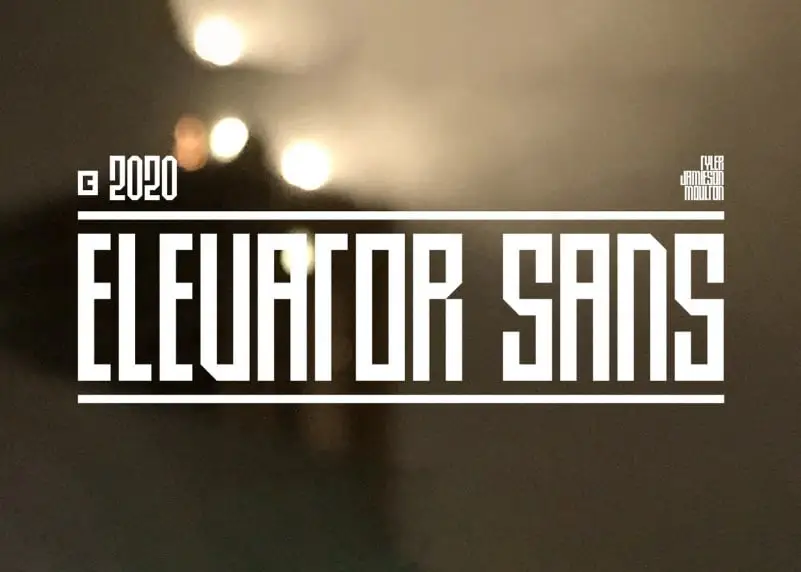
Elevator Sans Serif Font – Download Grátis
Se você busca uma futurista fonte sans-serif com estrutura única y que enaltece os elementos modernos, Elevator Sans Serif pode ser a escolha perfeita para você. Essa fonte é romanceada e timeless, mas também minimalista, um todo em maiúsculas de sans serif que brilha em qualquer contexto. É uma fonte casual e moderna, com aparência levemente mais informal para projetos variados. Suas características modernas dão ao design um toque leve e atual. Pode ser usada como título, logomarca ou citações, ou mesmo como parceira de outras fontes. Elevator Sans Serif também suporta múltiplas línguas. Esta é uma fonte semicompromissada que combina o estilo com a praticidade, tornando-se um recurso valioso para qualquer designer em busca de algo único e moderno.